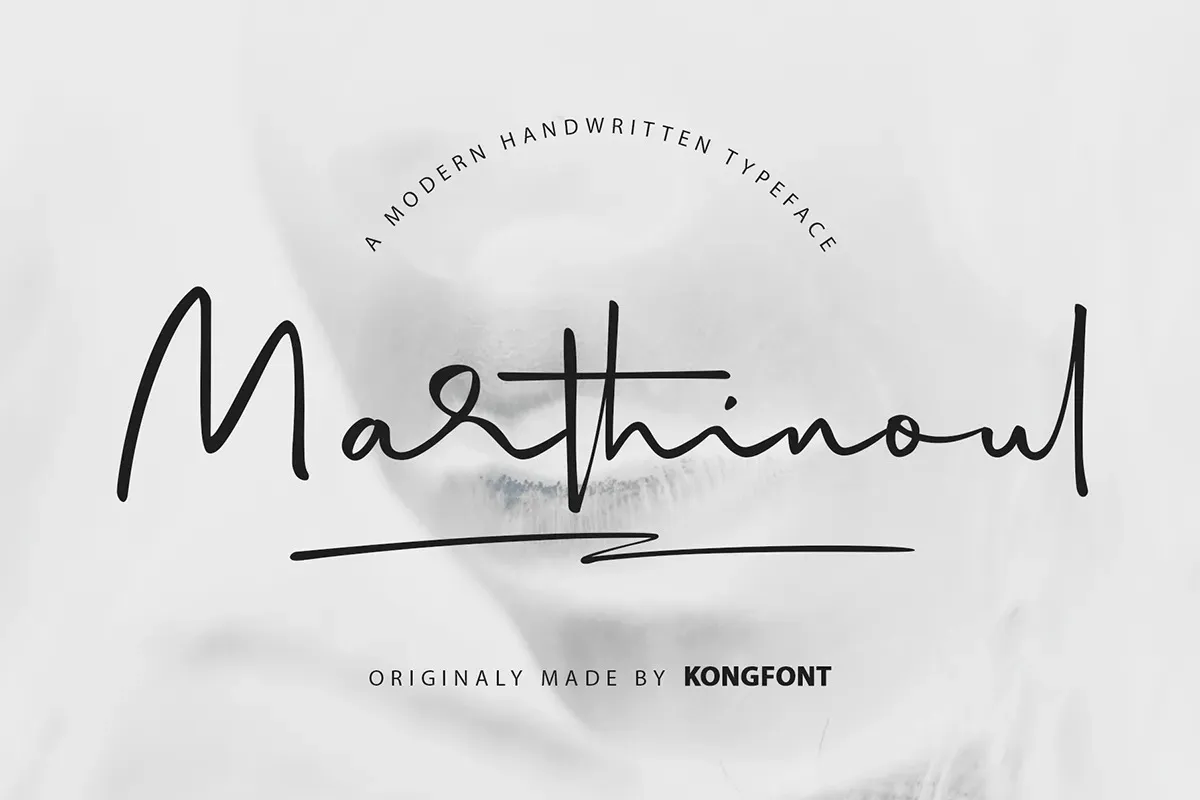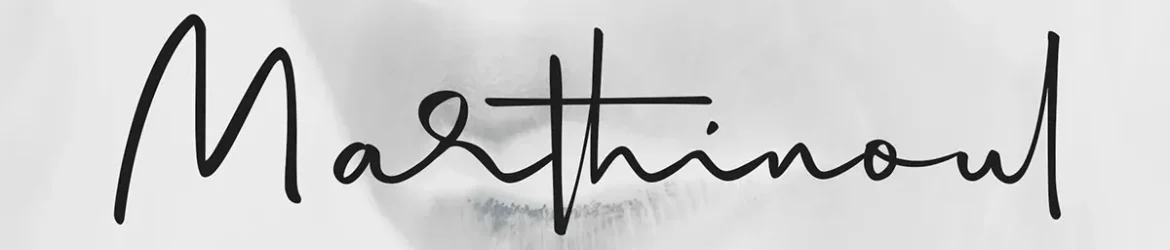
Marthinoul Font – Download Grátis
Esta é uma fonte script elegante e delicada criada pelo designer Kong Font. Ela possui um estilo limpo, fino e suave, perfeitamente adaptável a qualquer projeto que busque dar ao seu design uma pitada de sofisticação. A Marthinoul está PUA encoded, o que significa que você pode acessar todos os caracteres e swashes facilmente. Seja para cartazes modernos ou gráficos digitais, esta fonte adicionará um toque de elegância e modernidade a qualquer projeto que você estiver trabalhando. Engaje-se com a Marthinoul em suas apresentações design; ela certamente será uma escolha popular!